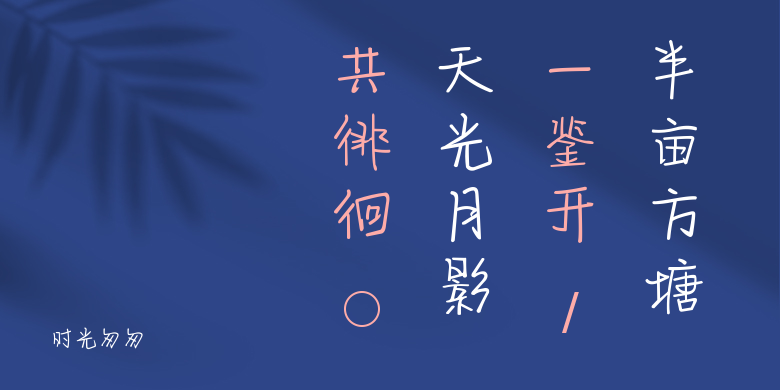
时光匆匆
时光匆匆,这款字体结构工整、笔画清晰,兼顾美观与易读性,适用于标题、正文、海报、包装、LOGO 等多种场景。字形优雅稳定,风格百搭耐看,适配日常排版与创意设计,让文字呈现更舒适、更具质感。时光匆匆一笔一画,皆是细节,以均衡的比例、流畅的线条打造舒适视觉体验,字形端正大气,风格简约现代。无论是商业设计、品牌宣传还是日常排版,都能轻松驾驭,让文字更有格调与力量。时光匆匆字体下载。